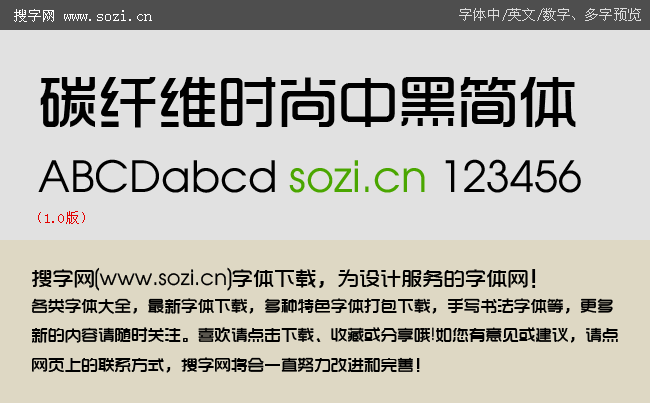
碳纖維時尚中黑簡體
本字體應開發(fā)者方正字體要求已下架,謝謝您的理解與支持!搜字網(wǎng)提供一款碳纖維時尚中黑簡體字體下載,該字體由時尚傳媒集團自主設計,是國內(nèi)首家以企業(yè)名稱命名的規(guī)范字體,時尚中黑字體整體字形筆畫均衡,風格現(xiàn)代,字體方中帶圓,端莊雅致,簡約時尚。適宜用于時尚類企業(yè)形象、產(chǎn)品名稱和廣告標題類用字。